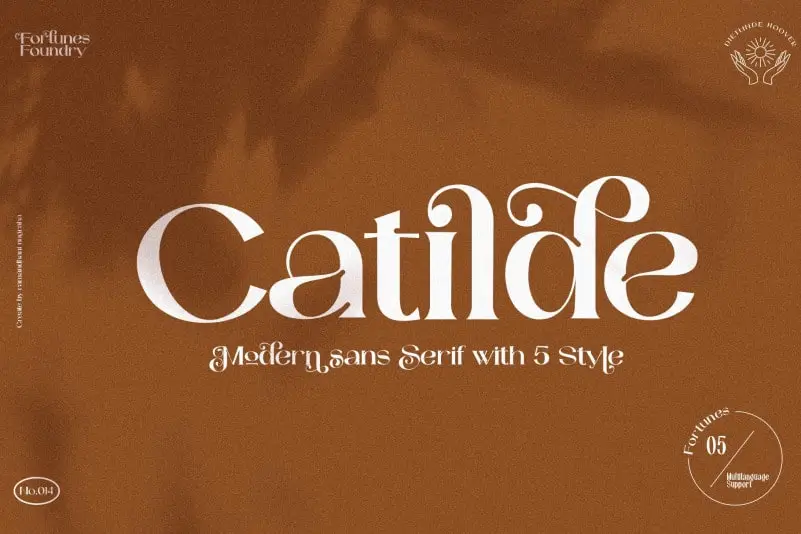
A Catilde Serif Font é uma escolha versátil para designers que buscam transmitir elegância através do tipo. Com seu formato serífero delicado e formas robustas, ela realça a sensação de luxo na impressão. Esta fonte oferece cinco estilos diferentes, adequados para múltiplas aplicações como identidade visual, revistas, logomarcas, convites, headlines e anúncios. Suas características proporcionam um toque suave que se assemelha a papel de seda, mas também tem forças suficientes para destacar em qualquer ambiente de design. Ideal tanto para designers iniciantes quanto para profissionais experientes, ela é uma fonte primorosa e versátil, perfeita para quem busca um touch de elegância nas criações gráficas.